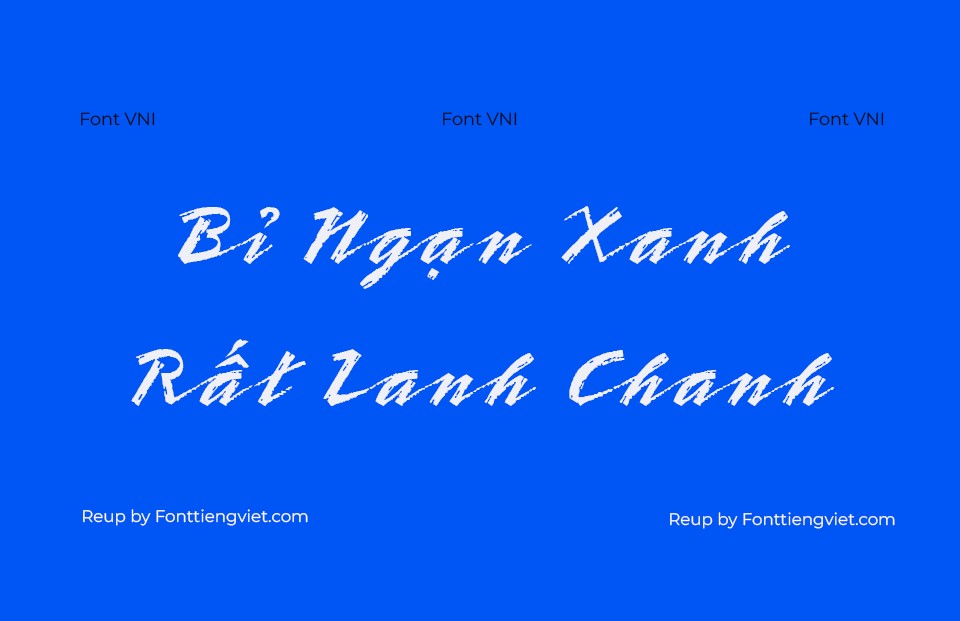
Trong kỷ nguyên số hóa, việc soạn thảo các tài liệu học tập, báo cáo hay thậm chí là đề thi chuẩn xác luôn là ưu tiên hàng đầu, đặc biệt đối với học sinh, sinh viên và giáo viên. Một trong những yếu tố quyết định đến tính chuyên nghiệp và thẩm mỹ của văn bản chính là Font Chữ. Khi nhắc đến các bộ font tiếng Việt phổ biến và dễ sử dụng nhất, không thể không kể đến bộ Font Việt hoá VNI Netbut. Đây là tập hợp các font chữ đã được điều chỉnh để tương thích hoàn toàn với bảng mã VNI, giúp người dùng gõ tiếng Việt một cách mượt mà và chính xác, loại bỏ hoàn toàn lỗi hiển thị ký tự (thường gọi là lỗi font) trong các bài tiểu luận hay luận văn tốt nghiệp quan trọng.
Giới Thiệu Tổng Quan về Bộ Font Việt hoá VNI Netbut
Bộ Font Việt hoá VNI Netbut thực chất là một nhóm font được chỉnh sửa từ các font gốc, nhằm mục đích duy nhất là phục vụ cho bảng mã VNI. Bảng mã VNI là một trong ba bảng mã tiếng Việt thông dụng nhất, bên cạnh Unicode và TCVN3 (ABC). Mặc dù Unicode đã trở nên phổ biến hơn trong thời gian gần đây, hệ thống VNI vẫn còn được sử dụng rộng rãi trong nhiều cơ quan, trường học và đặc biệt là trong các tài liệu cũ hoặc các phần mềm chuyên ngành. Sự ra đời của Font Việt hoá VNI Netbut đã giải quyết triệt để vấn đề đồng bộ hóa ký tự, đảm bảo rằng dù bạn đang soạn thảo báo cáo khoa học hay thiết kế bài giảng, văn bản của bạn vẫn giữ được sự rõ ràng và nhất quán. Các font VNI thường có tên bắt đầu bằng “VNI-“, ví dụ như VNI-Times, VNI-Helve, tạo sự dễ dàng trong việc nhận diện và lựa chọn.
Lợi Ích Của Việc Sử Dụng Font VNI Trong Học Tập và Thi Cử
Đối với học sinh, sinh viên chuẩn bị cho các kỳ thi tốt nghiệp hoặc cần nộp các báo cáo học thuật, việc sử dụng font VNI mang lại nhiều lợi ích thiết thực. Thứ nhất, nó đảm bảo tính tương thích cao với hệ thống máy tính cũ hoặc các phần mềm đặc thù được sử dụng tại trường học hoặc các trung tâm khảo thí. Thứ hai, các font VNI, đặc biệt là phiên bản Netbut, thường có nét chữ rõ ràng, dễ đọc, giúp giám khảo và giáo viên dễ dàng chấm điểm và theo dõi nội dung. Việc biết cách quản lý và sử dụng thành thạo các bộ font này là một kỹ năng tin học văn phòng cơ bản nhưng cực kỳ quan trọng, giúp các bạn tránh được những rắc rối không đáng có về định dạng văn bản khi nộp bài cuối kỳ. Hơn nữa, việc sử dụng chuẩn font cũng thể hiện sự chuyên nghiệp trong cách trình bày tài liệu của người học.
Tóm lại, bộ Font Việt hoá VNI Netbut không chỉ là một công cụ hỗ trợ gõ tiếng Việt thông thường mà còn là một phần không thể thiếu giúp các bạn học sinh, sinh viên tạo ra những tài liệu học tập, báo cáo và luận văn chuyên nghiệp, đạt chuẩn. Việc nắm vững cách sử dụng các bảng mã và bộ font tương ứng sẽ nâng cao đáng kể kỹ năng tin học văn phòng, mang lại lợi thế lớn trong học tập và công việc sau này. Hãy chắc chắn rằng bạn đã cài đặt đầy đủ bộ font này và luôn kiểm tra lại bảng mã trước khi bắt đầu soạn thảo để đảm bảo văn bản của mình không mắc phải bất kỳ lỗi hiển thị ký tự nào. Sử dụng Font Chữ VNI chất lượng cao như VNI Netbut là bước đầu tiên để đạt được sự hoàn hảo trong trình bày tài liệu.